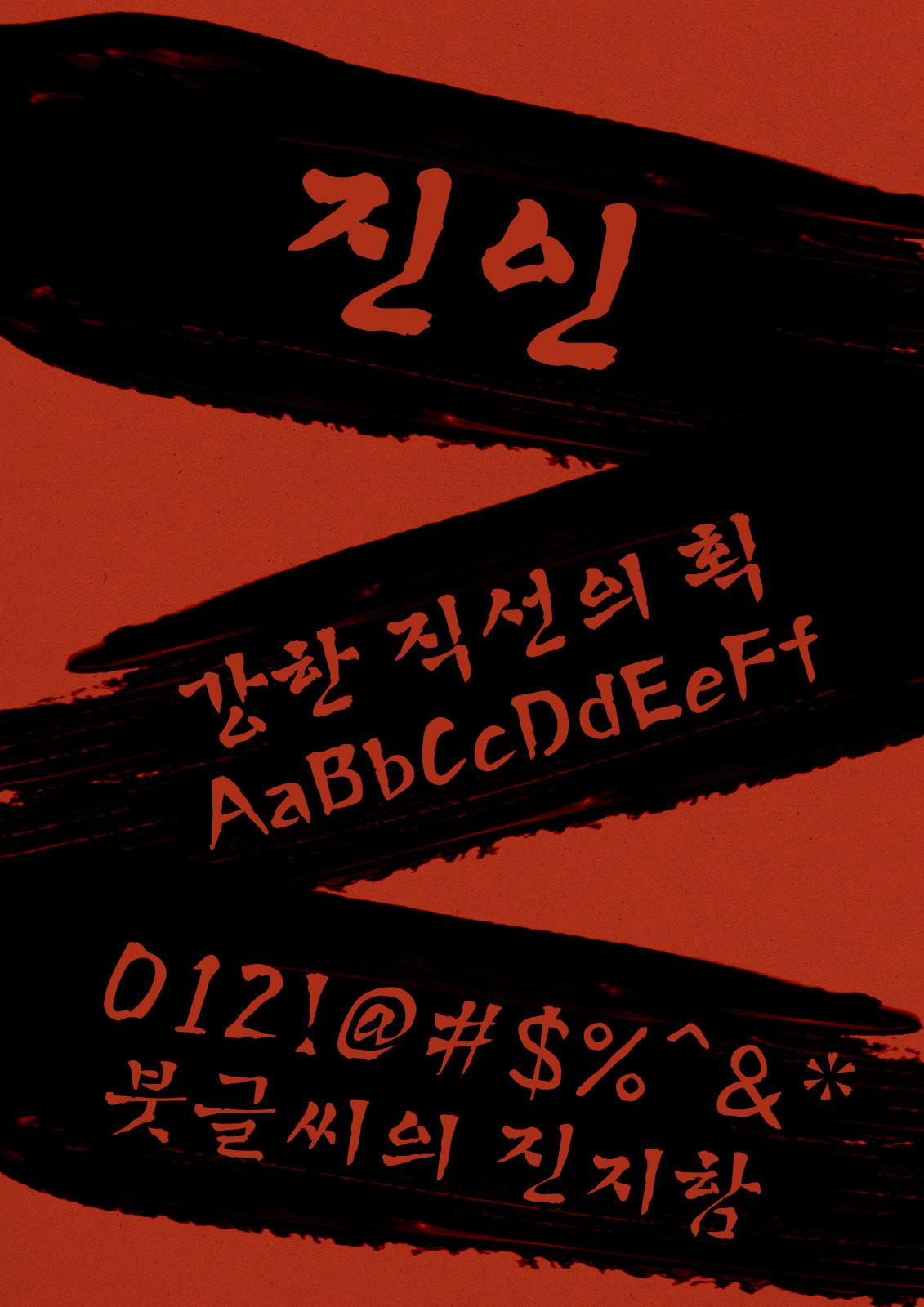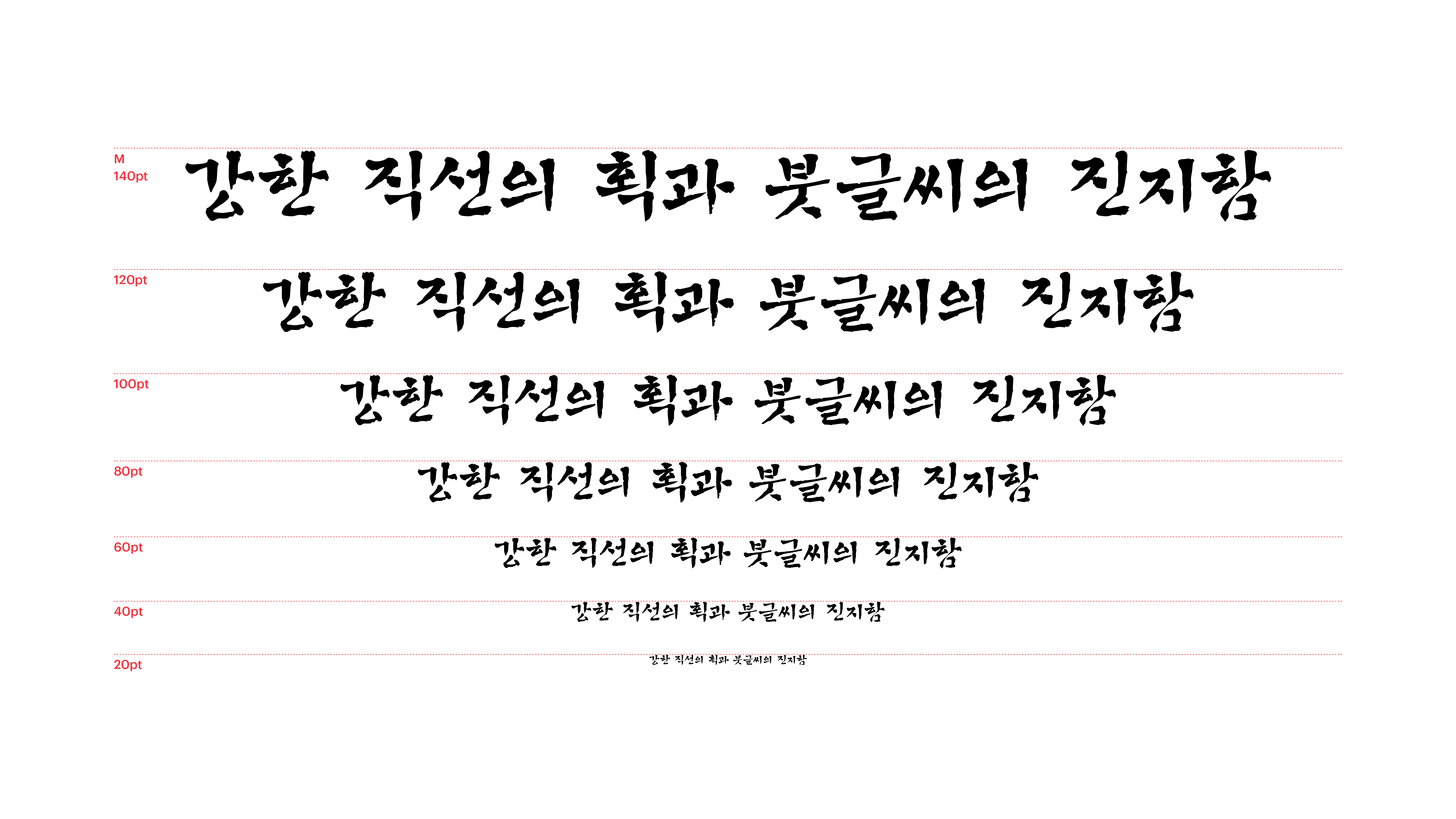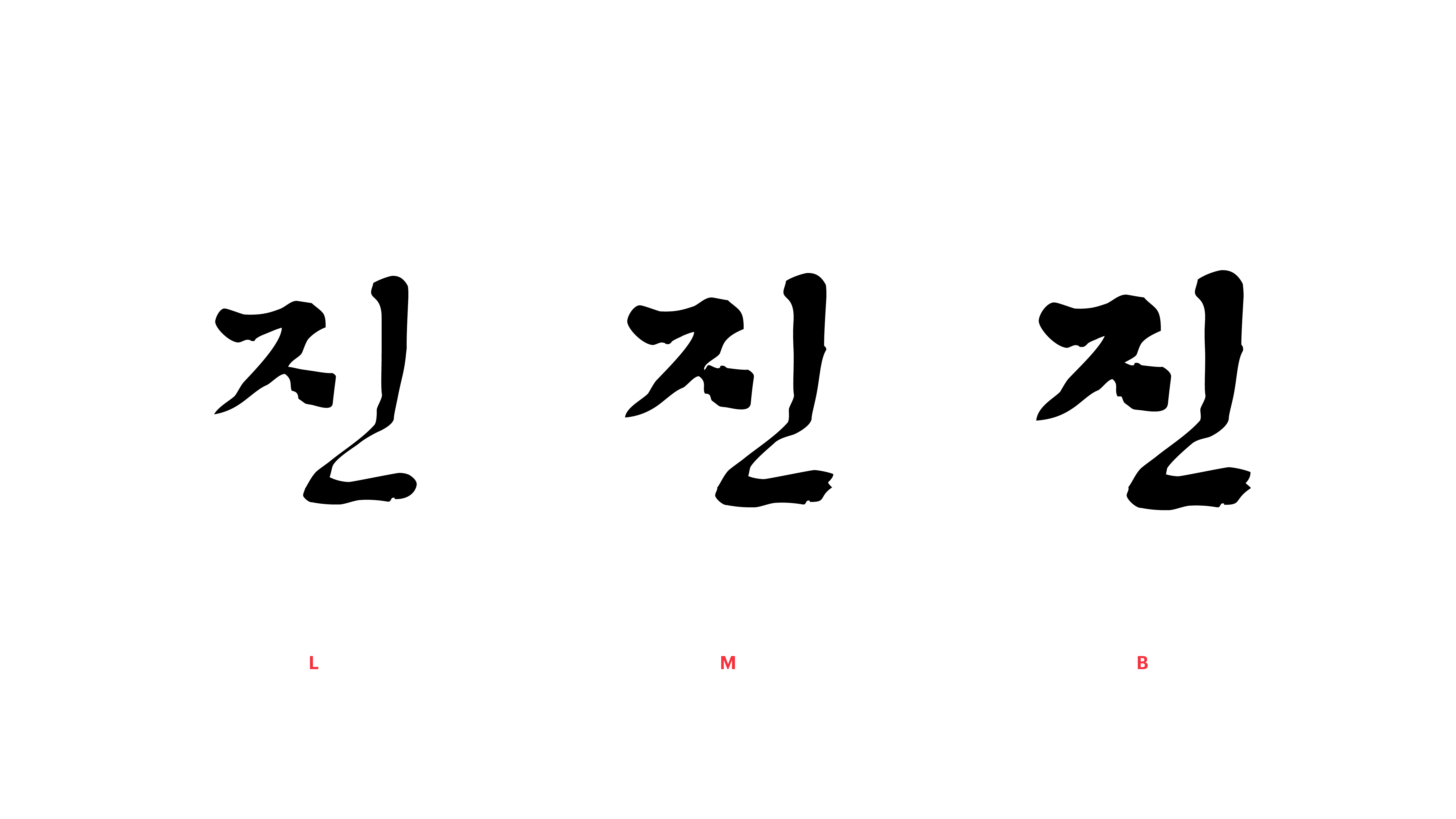
진인
Yoon 진인
공복 유산소, 저녁 여섯 시 이후 금식, 전화 영어 열심히 하기 등. 늘 너무 쉽게 작심삼일이 되어버리고 마는 우리의 다짐들을 어떻게 하면 좋을까요? 결심이 선 순간 진인체를 선택하고 다짐을 옮겨 적어보세요. 강한 직선의 획에 붓글씨의 특징을 더해 완성한 진지한 이 폰트가 계획 실천의 강력한 동반자가 되어줄 거예요.